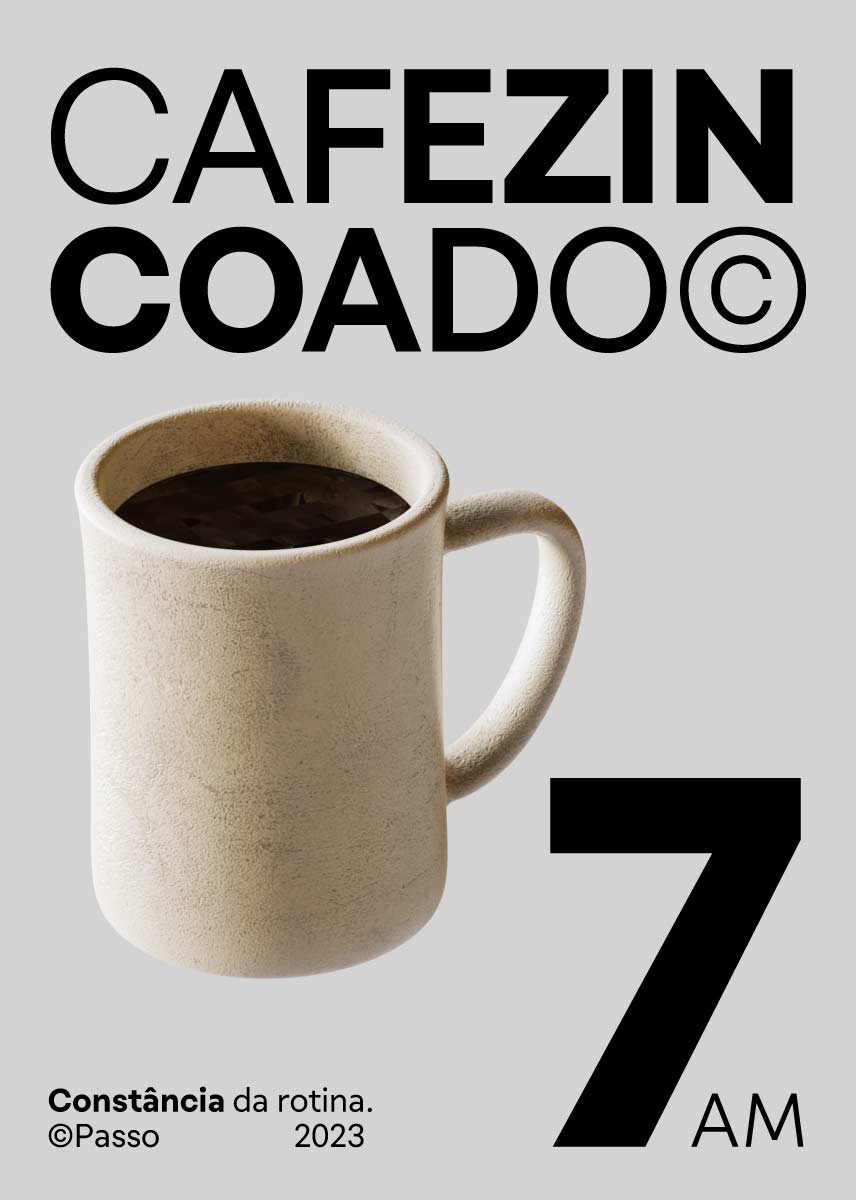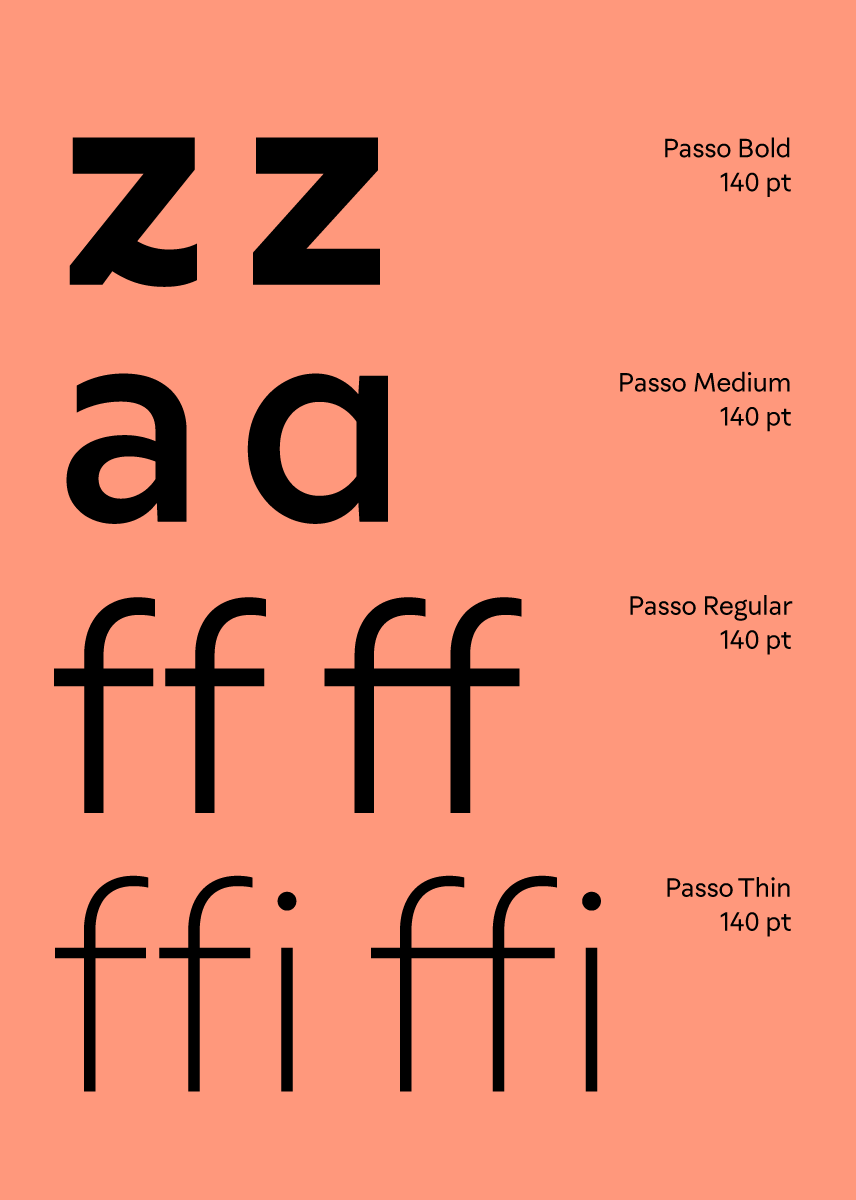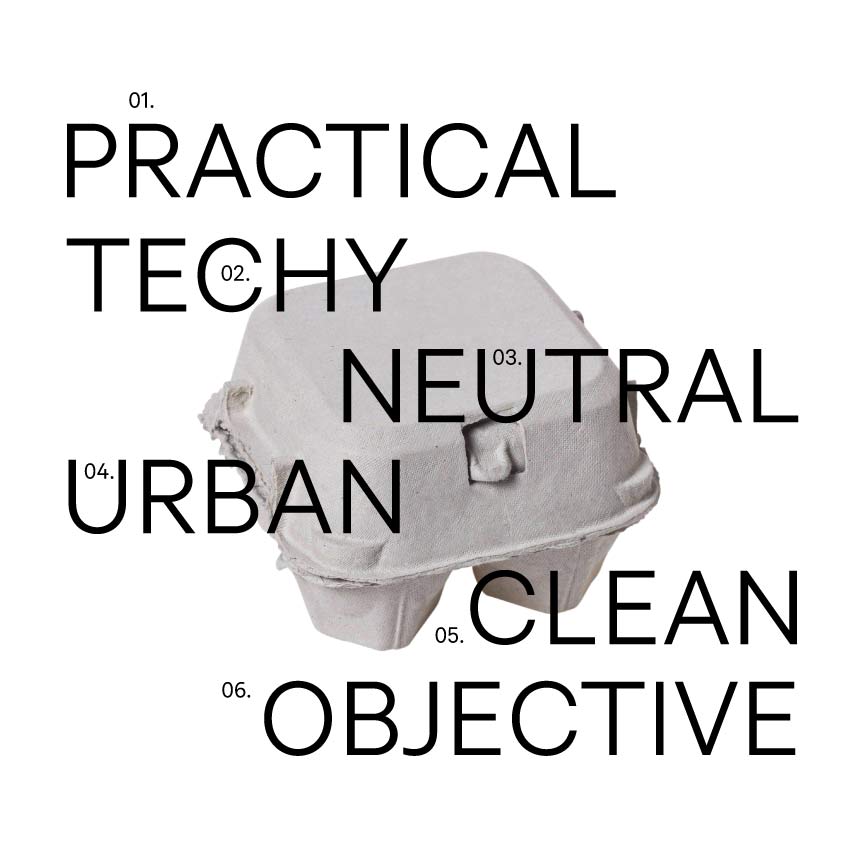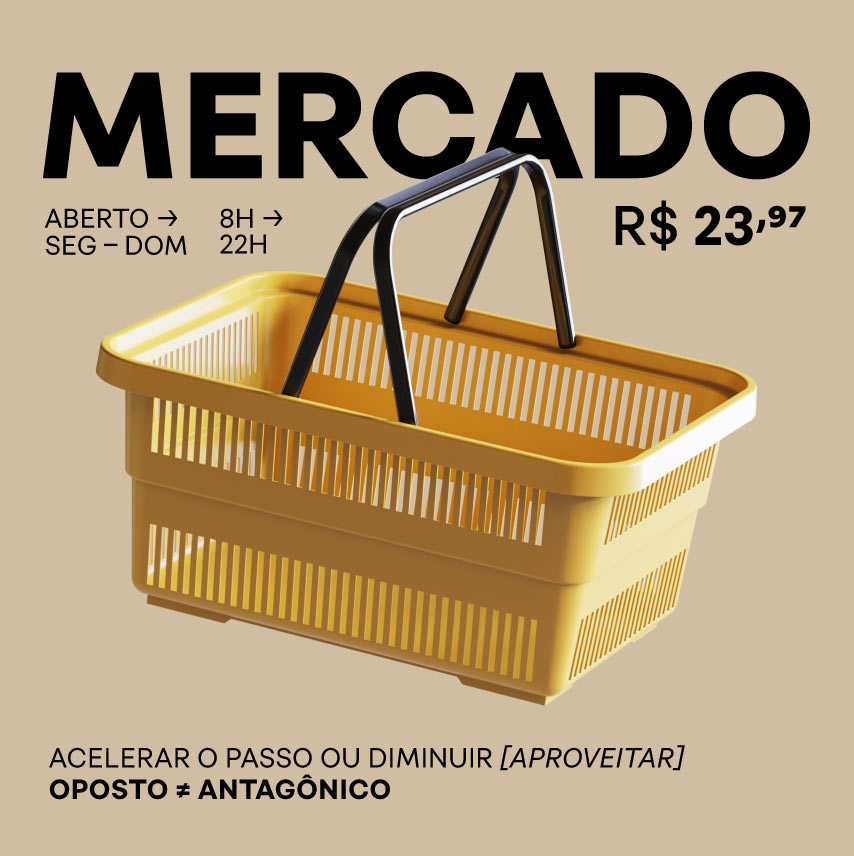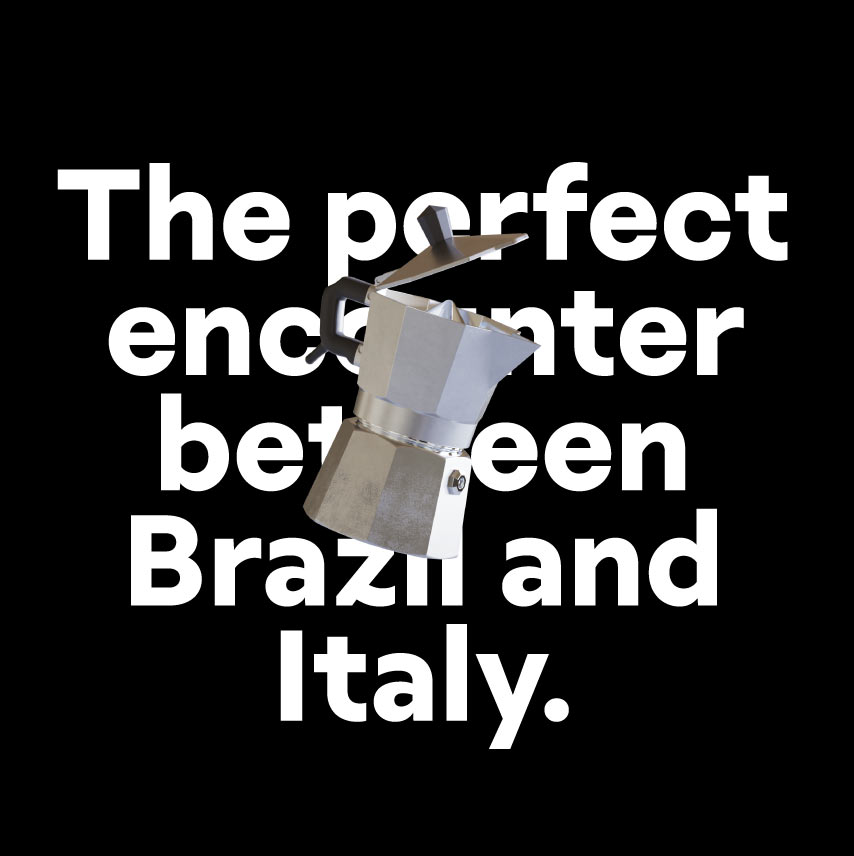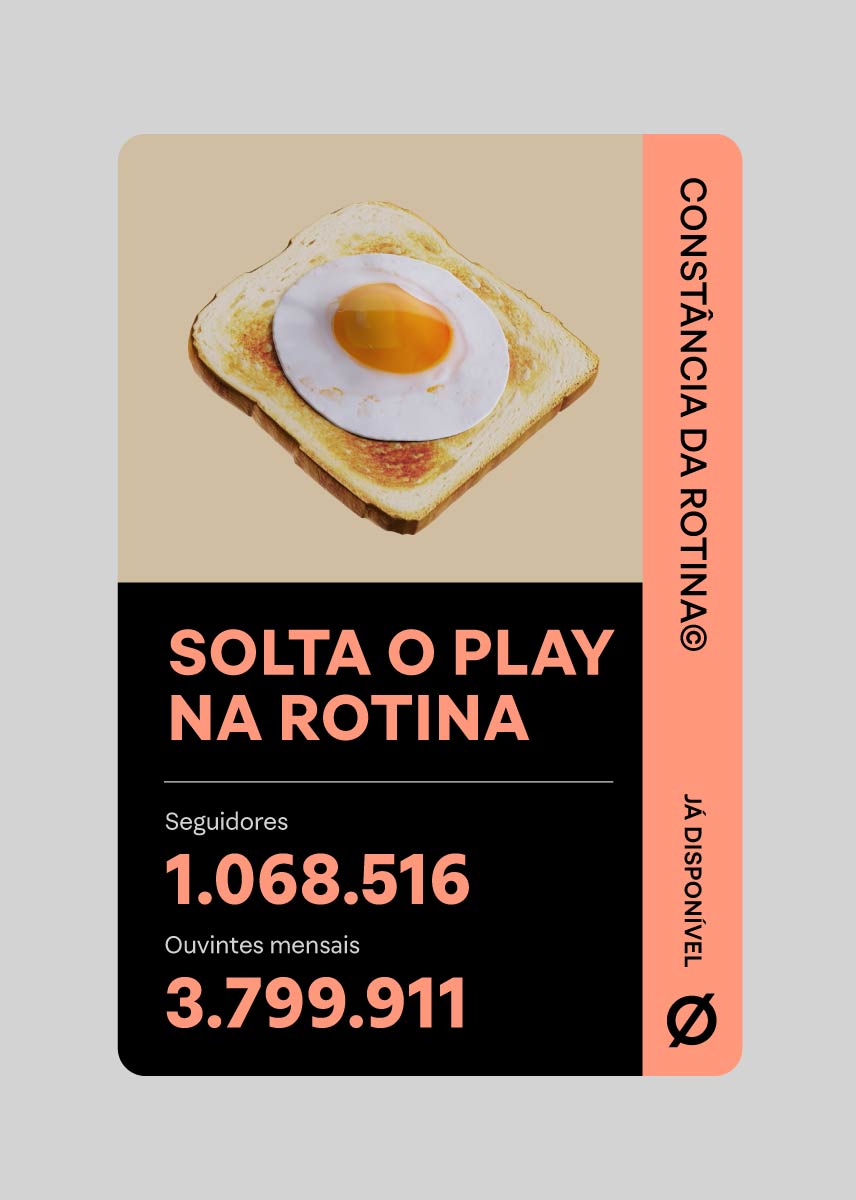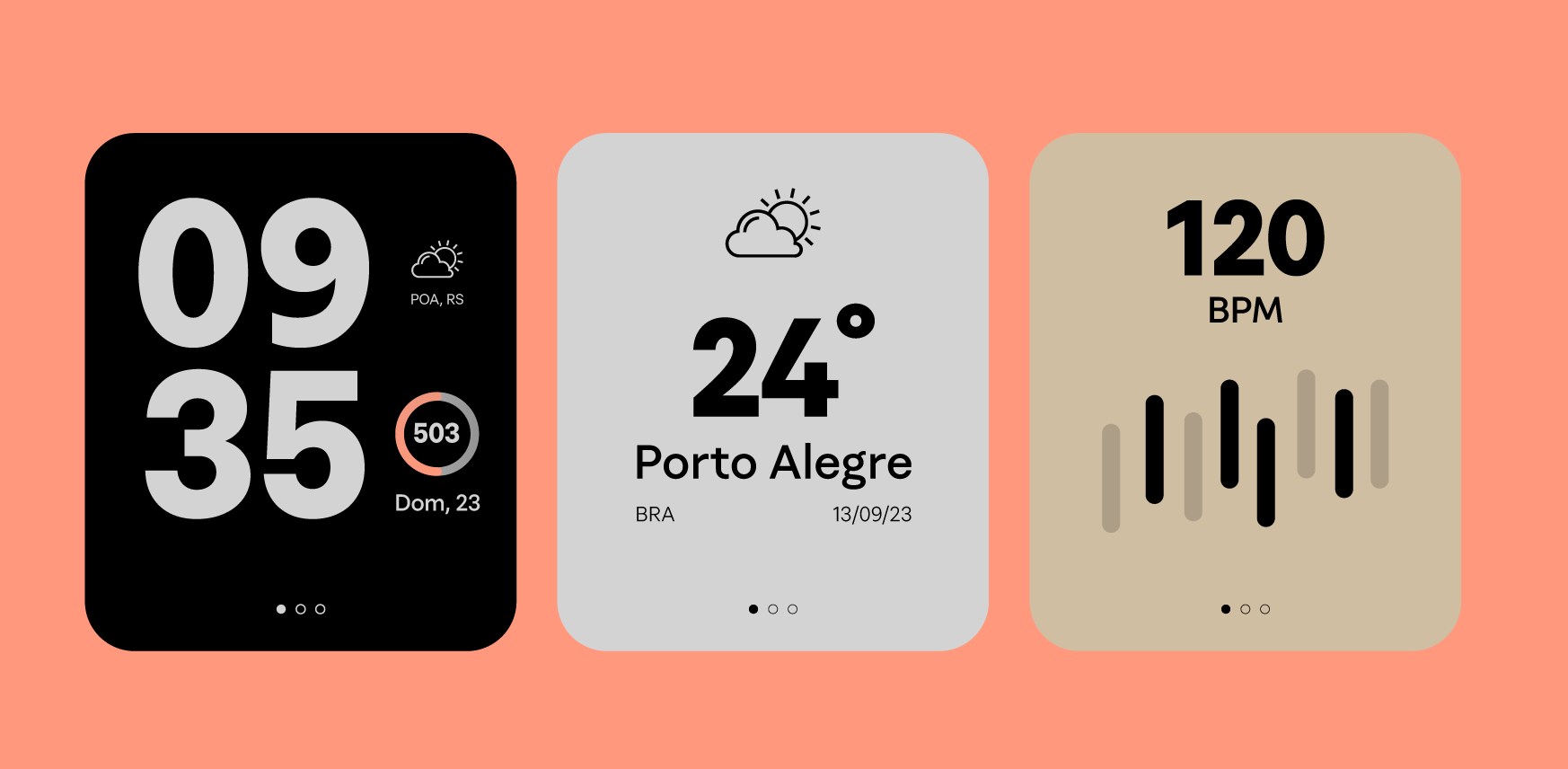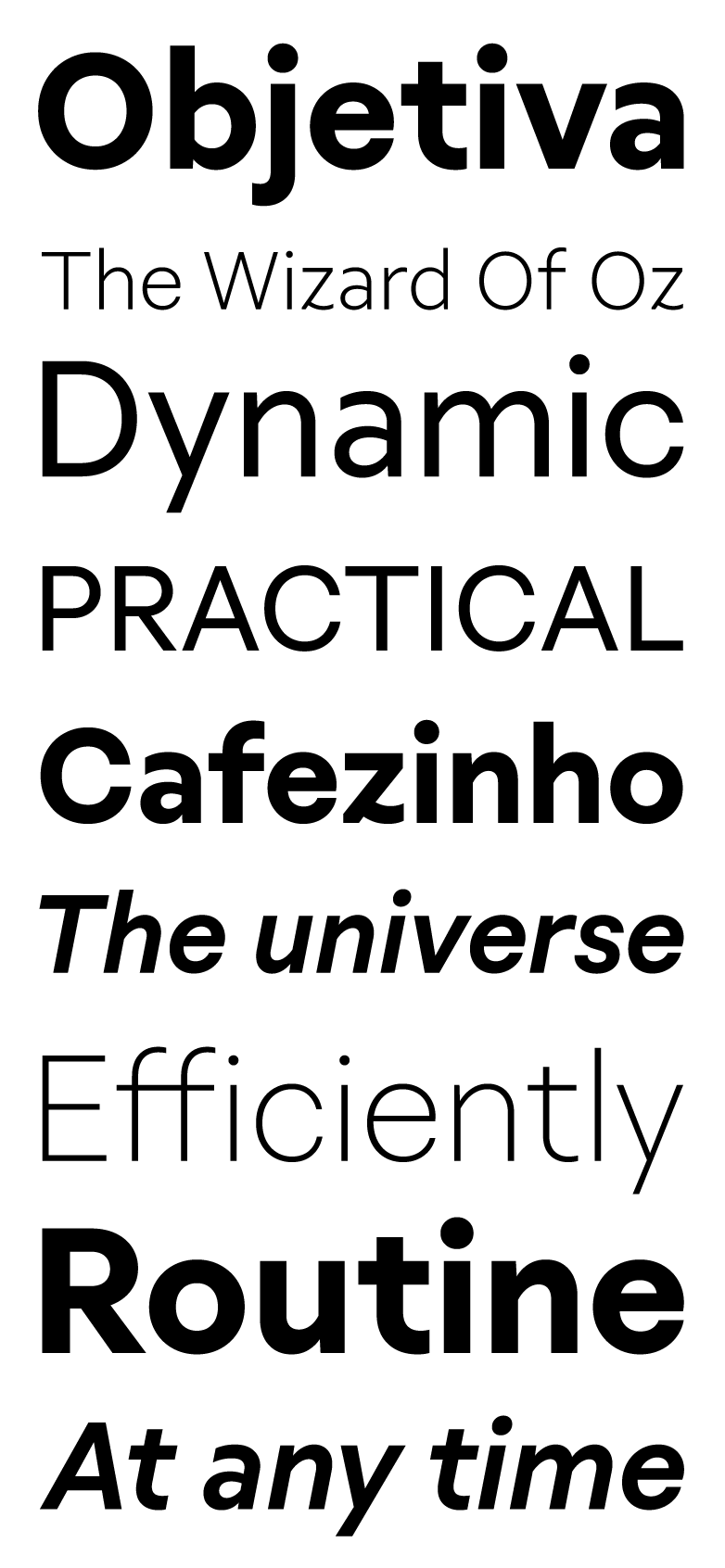
How to do nothing
Folhas crescendo no apartamento
FORM FOLLOWS FUNCTION
It will help you solve various challenges without raising existential questions.
Use what’s helpful
The work is done when you feel it is
Temporary rules
The universe never explains why
O suave respirar na meditação em silêncio. Galáxias se expandindo no universo. Folhas crescendo no apartamento. Uma coisa conecta tudo isso: estar vivo é estar em movimento.
No dia a dia aceleramos o passo. Rotina, forma seguindo a função. De olho no passeio do final de semana. Ou melhor, desta tarde? Por que não?
Foi pensando nos diferentes ritmos da vida que criamos as tipografias Passo e Passeio, lideradas pela Ana Laydner. Com um pé na frente do outro, de passo em passo, vamos desenhando e vivendo.
A Passo tem a constância da rotina. Monolinear, com baixo contraste, ela entrega a mensagem de forma eficiente e direta. É o cafezinho para repetir a qualquer hora do dia. Vai te ajudar a resolver vários desafios sem levantar questões existenciais. Já a Passeio carrega as nuances de um alto contraste e algumas terminações serifadas. É elegante e vai tomar a sua atenção. Te convidar para sair ou cair no mar. Abrir um espumante. Sair para viajar. A parar e celebrar.
São desenhos opostos mas não antagônicos: compartilham da mesma construção e métricas verticais, ou seja, podem ser combinadas e misturadas pra refletir a montanha-russa que é a vida.
Acelerar o passo ou diminuir para passear, há sempre uma hora e um lugar.